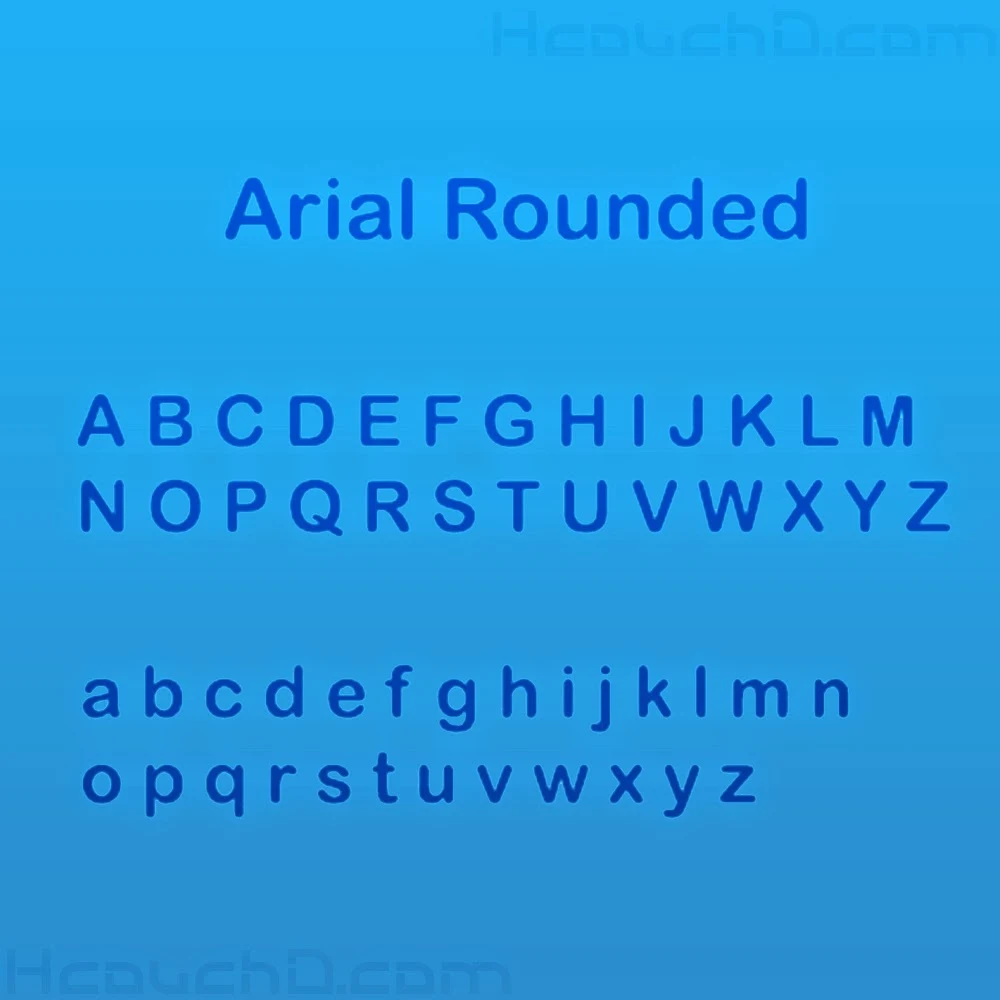
خط Arial rounded خط بسيط و قوته في بساطته ، و سبق أن استعملناه في درس ” درس 36 : كيفية إنشاء تأثير نص الأرقام الملونة 2014 في فوتوشوب + ملف PSD” ، يمكنك تحميل هذا خط من رابط أسفله …